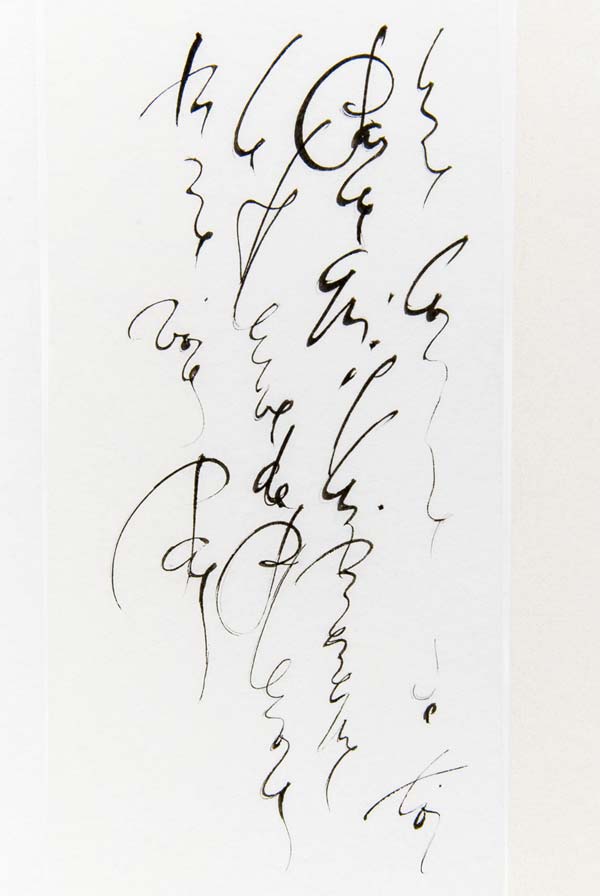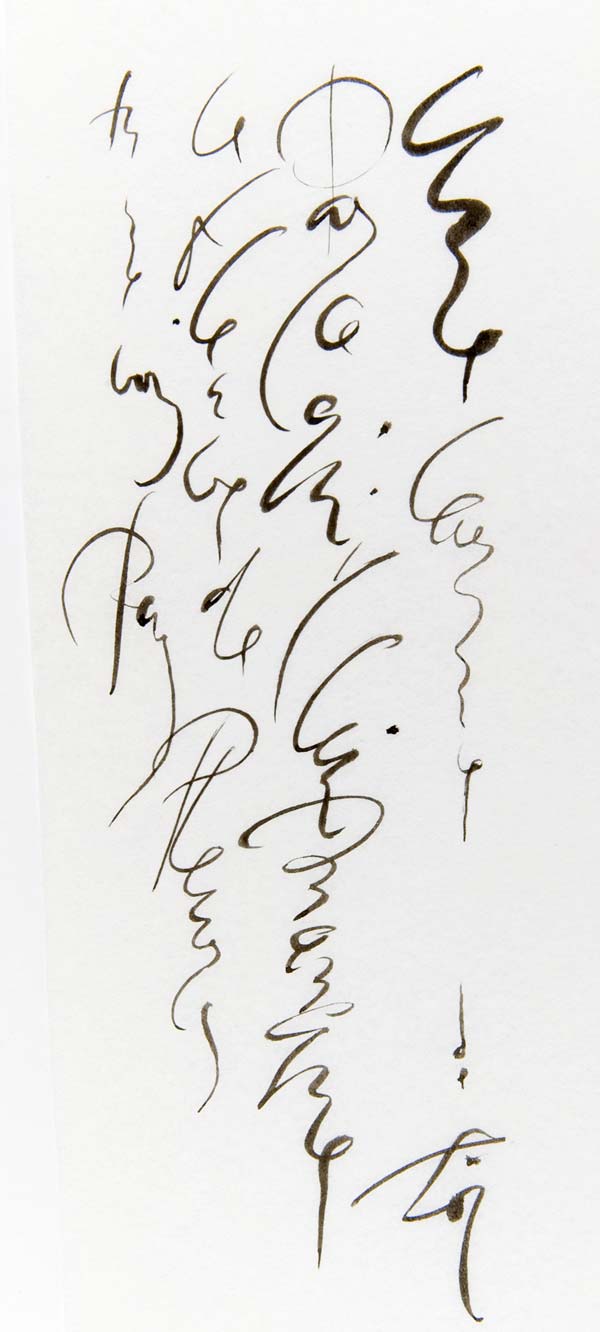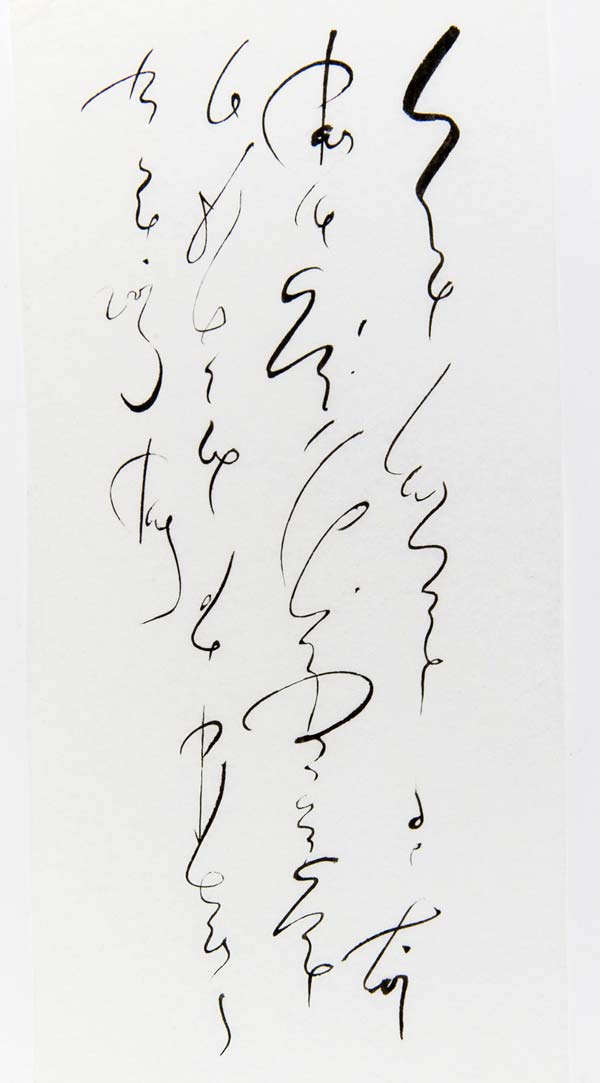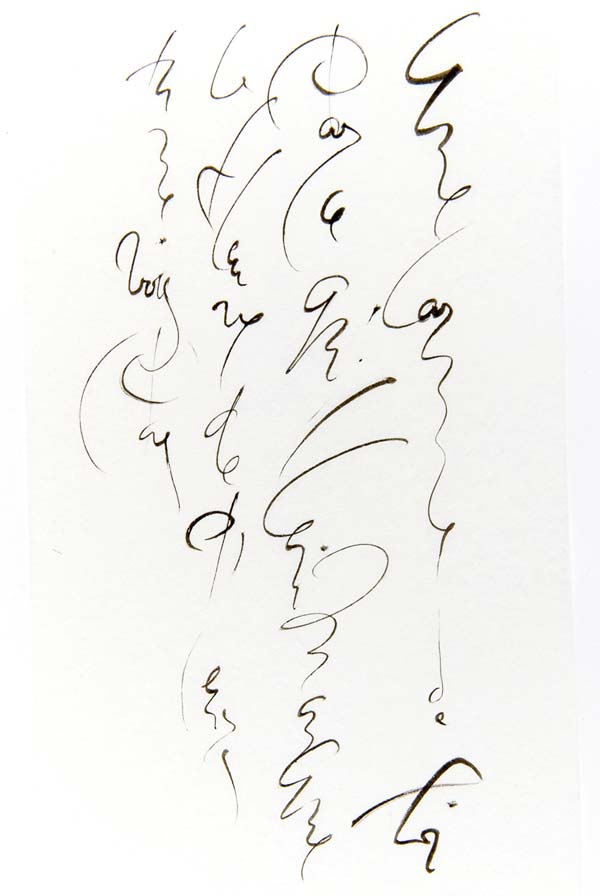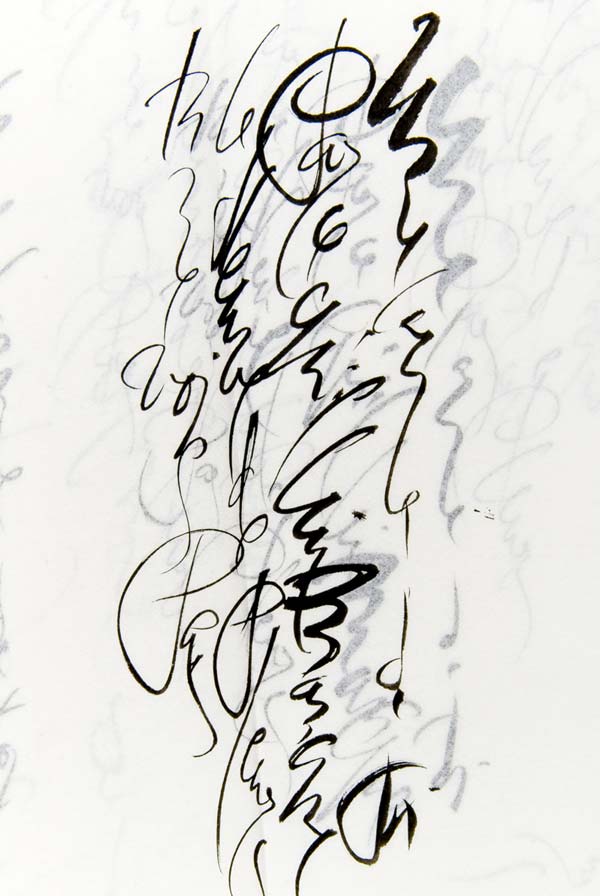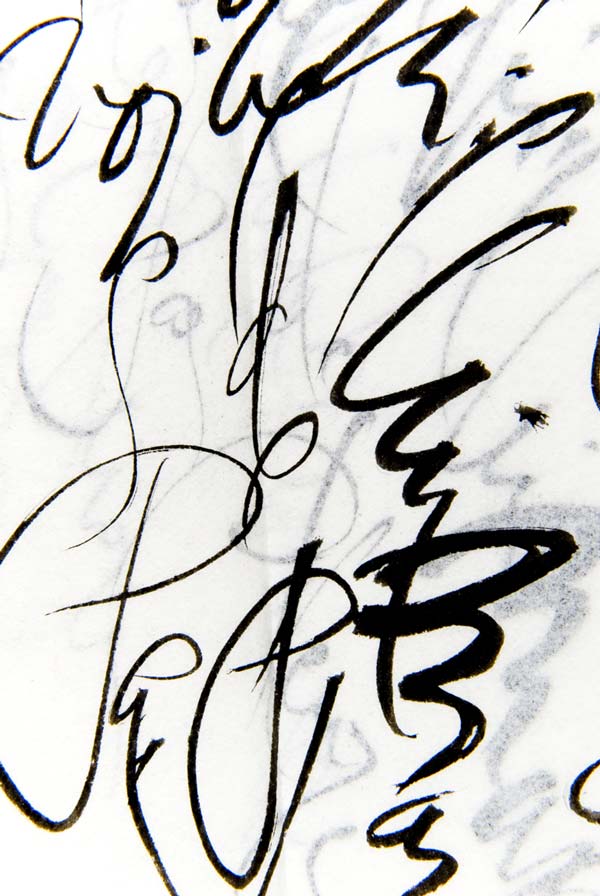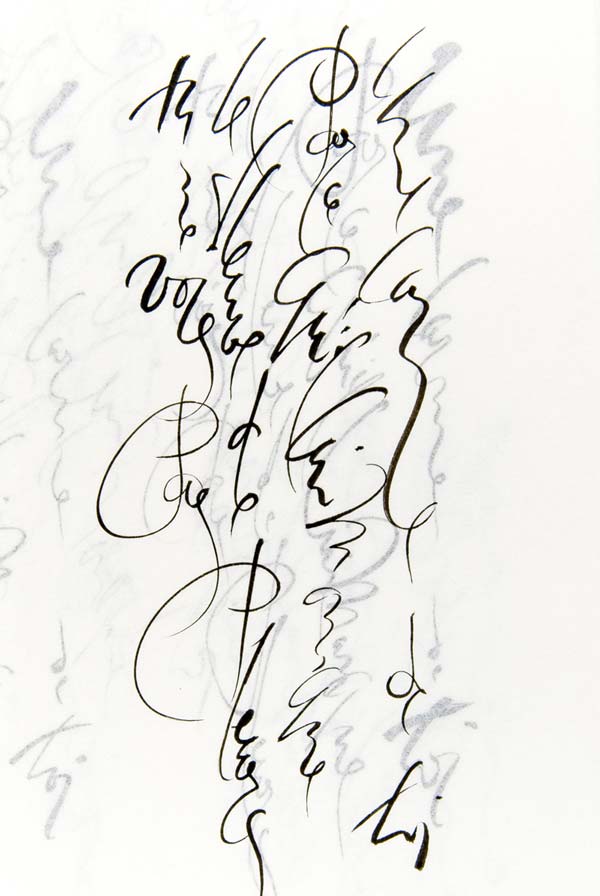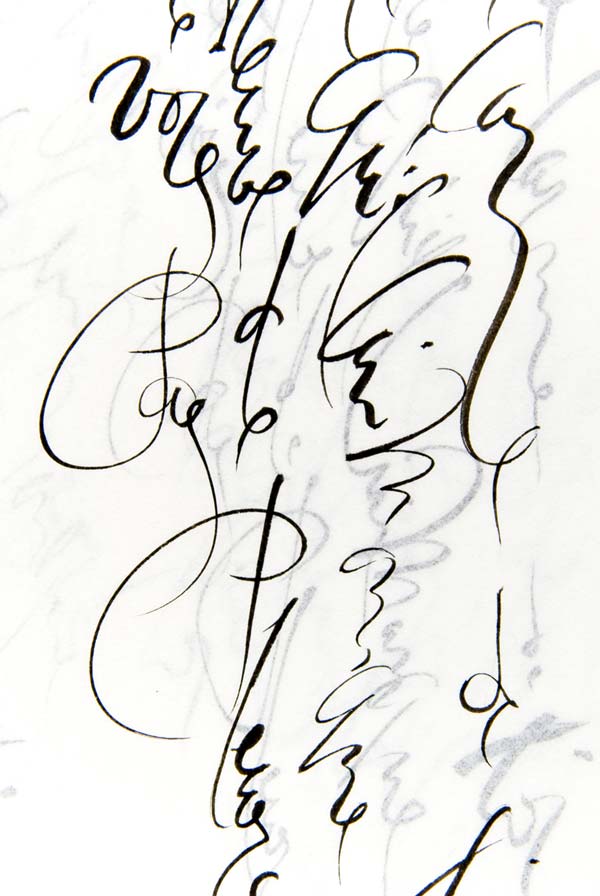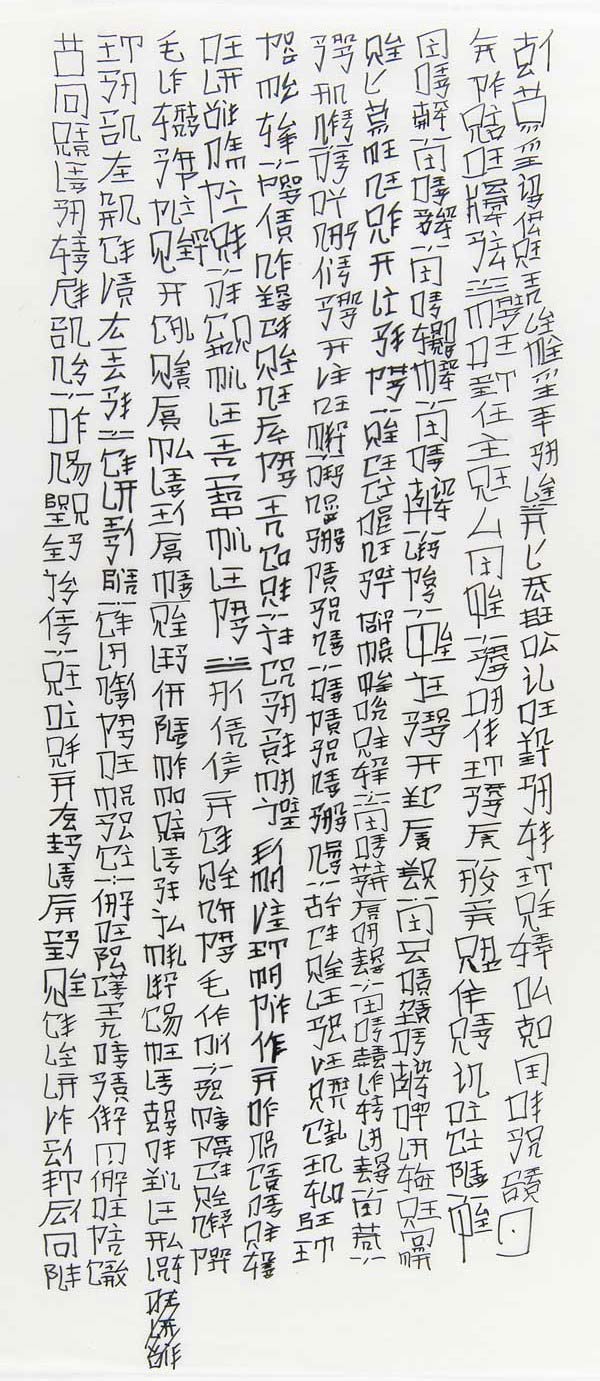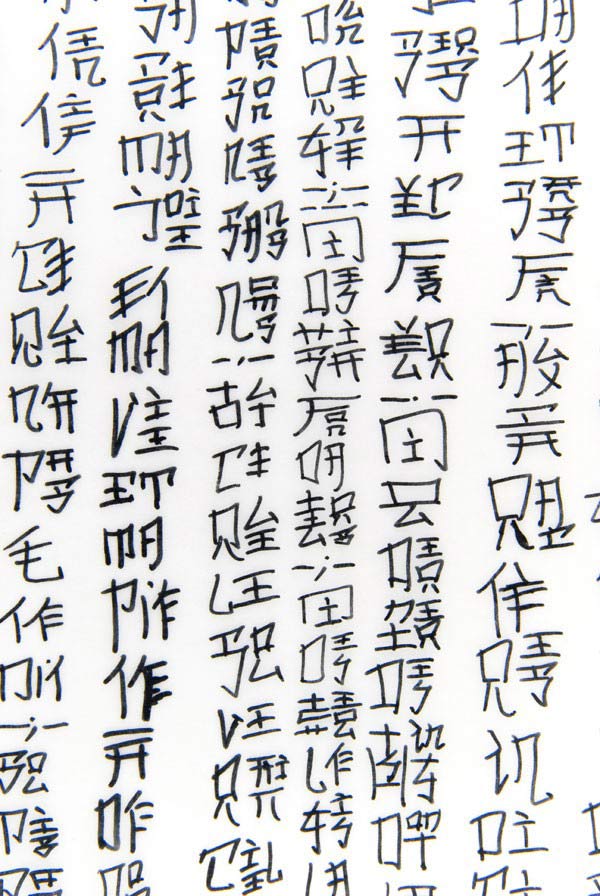
Quand la Suisse rencontre la Chine | Hommage à Soheil Azzam, graphiste (reloaded)
J’ai rencontré Soheil Azzam un jour de février dernier, (il y a deux ans de cela). Cela faisait longtemps qu’il laissait des commentaires très fouillés sur des sujets aussi variés que la calligraphie ou la mise en page, puis un jour on s’est téléphoné. Il habite en Suisse et rendez-vous fut pris pour un dîner parisien auquel assista également Jonathan. La vie de Soheil n’est pas simple, Moyen Orient puis la Suisse, et enfin la Chine. Ah l’amour, toujours l’amour en roulant les rrrr à la hongroise. Il fut pris de passion à la fois pour une femme et pour son pays, mais surtout pour la calligraphie. Après des études laborieuses helvètiques, il s’expatria qq temps en Chine où il apprit également les rudiments de la langue. Puis il revient dans la cuvette montagneuse pour y exercer finalement son métier avec une rigueur et une fantaisie enpreintes d’une très grande sensibilité. Il m’a laissé quelques pdf que j’ai traduit en galerie de son œuvre graphique et aussi des carnets de notes en vrac que j’ai photographié pour l’intérêt qu’ils témoignent pour l’entrainement constant à l’écriture et au tracé calligraphique.
Soheil a écrit un livre que l’on peut consulter sur son website dont voici résumé l’introduction de l’introduction:
«Après qu’il eut tenu au peintre ce discours, Tch’eng Wang déclara que désormais on crèverait les yeux à tous les peintres et à tous les sculpteurs qui ajouteraient une forme aux formes du monde, et qu’on percerait les oreilles et couperait les mains à tous les musiciens qui ajouteraient un son aux sons du monde. Il condamna l’art sous toutes ses formes car, dit-il, l’art n’est qu’orgueil et imperfection.»
Histoire vraie quoique imaginaire de Tch’eng Wang le Fou (chapitre II)
Galerie en hommage à l’œuvre graphique de Soheil Azzam
Le travail de Soheil est à fois empreint du geste pur et de l’analyse sémantique auquel il s’adonne à chaque chantier. Délicatesse, sensibilité, une sainte horreur des guimmicks à la mode, Soheil tend par son travail vers l’essentiel. Les formes utiles et le rythme d’une mise en page qui de déséquilibre en déséquilibre et retombe à chaque fois sur ses fondamentaux. Des règles de mise en pages oui, à condition d’user et d’abuser de les pervertir. A la fois graphiste, graveur, peintre et calligraphe, Soheil ne dément pas l’image que nous avons du graphiste contemporain, infiniment plus artiste qu’à l’époque des années 50 mais un souci rare pour la lisibilité, la vraie, celle qui donne envie de lire.
essais calligraphiques, carnets de notes de Soheil
recherche de logotypes et d’image de marque, carnets de notes
essais calligraphiques, carnets de notes de Soheil
essais calligraphiques, carnets de notes de Soheil. Le travail calligraphique de Soheil n’a rien d’aussi perfectionné que celui d’un Claude Mediavilla. Cependant il est rare de voir un calligraphe partir d’une nécessité d’écriture dans la langue chinoise tout simplement pour se faire comprendre par ses nombreuses fréquentations professionnelles de Pékin ou Shangaï. Pour Soheil calligraphier n’est pas seulement donc une gymnastique gestuelle mais aussi une tentative de faire sien une langue dont la compréhension ne peut que nous échapper si l’on pénètre pas au tréfonds de la représentation du verbe. Ainsi le tracé est ici bien plus un exercice d’écriture utile et fonctionnel qu’une gesticulation gratuite et purement esthétique.
essais calligraphiques, carnets de notes de Soheil
recherche de logotypes et d’image de marque, carnets de notes
http://www.typogabor.com/Media/soheil_training_blog/Soheil_DSC_8456.jpgessais calligraphiques, carnets de notes de Soheil, où l’on se souvient enfin des origines orientales de l’artiste. Tourmenté mais tellement sensible.
essais calligraphiques, carnets de notes de Soheil, où l’on comprend que le tracé de l’écriture chinoise procède de principes d’équilibre et de structuration de l’espace graphique, proches de nos règles de mise en pages occidentales.
essais calligraphiques, carnets de notes de Soheil
essais calligraphiques, carnets de notes de Soheil. Exercices réalisés sur du papier bible de 40 gramme.